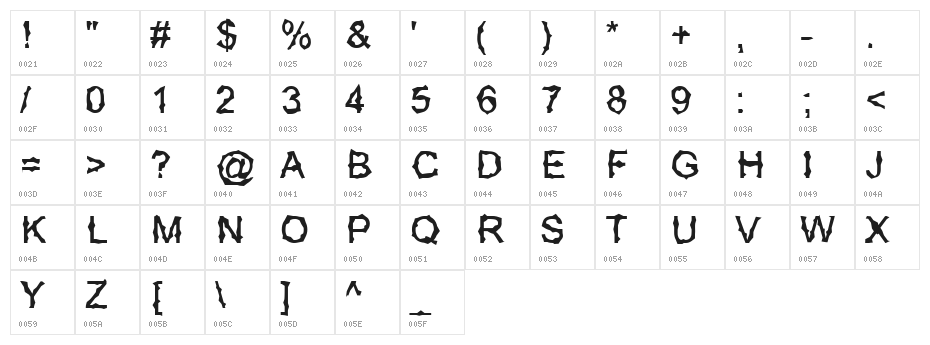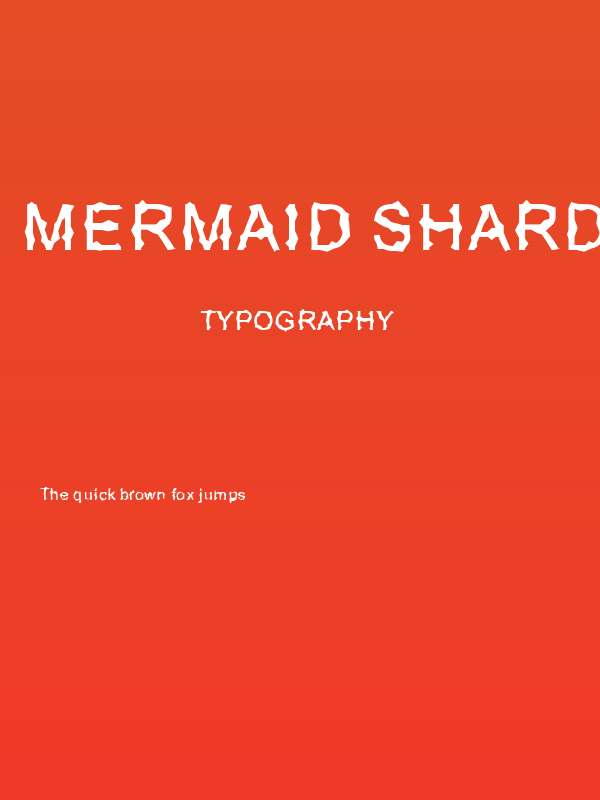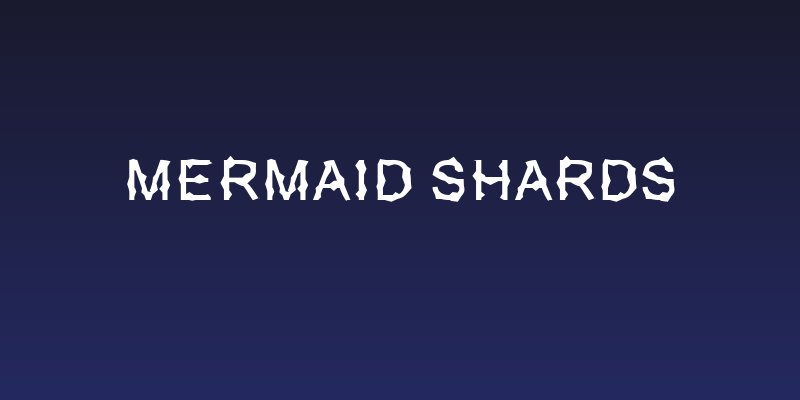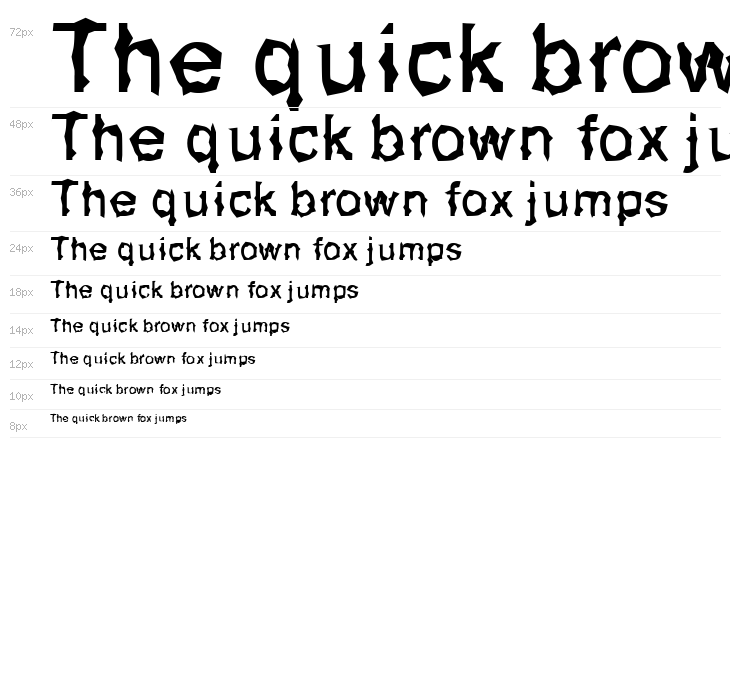
Mermaid Shards Font
✎ Thick
MERMAID-SHARDS Groß
MERMAID-SHARDS Kleinbuchstaben
MERMAID-SHARDS Anderer Schreiben
| Name | Mermaid Shards |
| Kategorien | Thick |
| Vorgeschlagene Projekte | Ideal for projects that require a bold and unconventional look, such as posters, album covers, or branding for edgy products. |